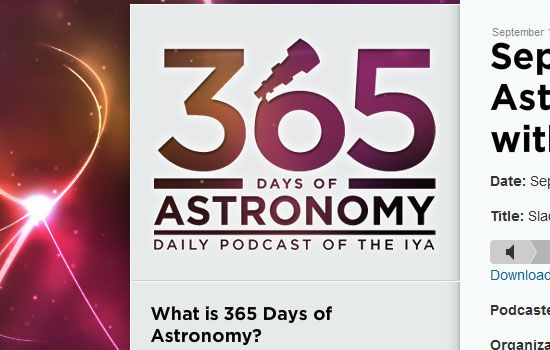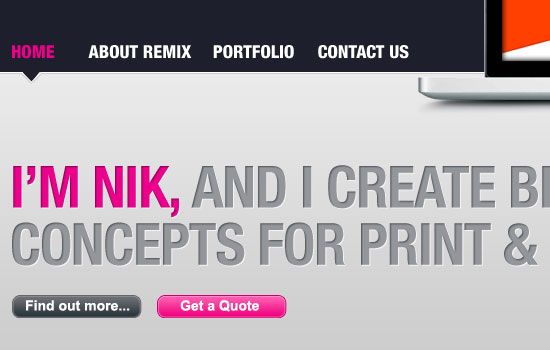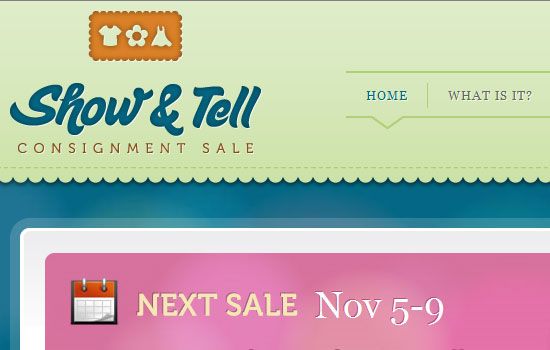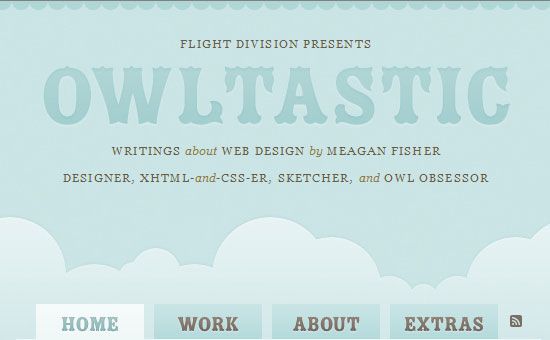
Existen muchas técnicas para poder adornar la tipografía de nuestro sitio. Una de ellas es el grabado de tipografía, un efecto para grabar la tipografía en una superficie, que también podemos crear con CSS3. Cuando esta técnica se usa de forma adecuada, nuestro sitio lucirá original y agradable a la vista. Tener inspiración para desarrollar esta técnica no viene mal, así que os mostraré a continuación una lista de bonitos ejemplos de grabado de tipografía:
1. Epic Event
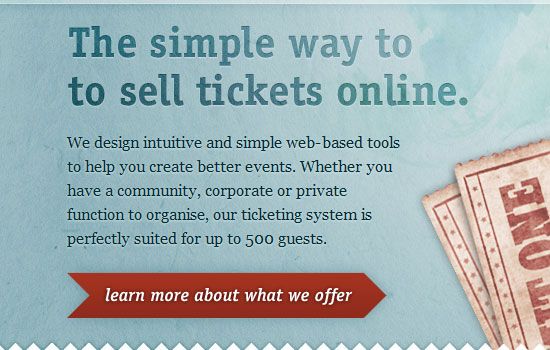
2. Remix Creative
3. Show & Tell
4. Graphik
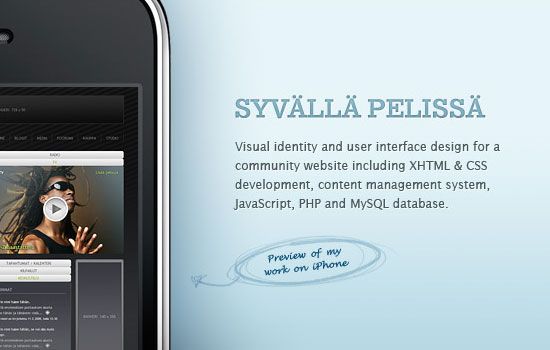
5. 365 Days of Astronomy
6. Owltastic
7. Sarah Longnecker
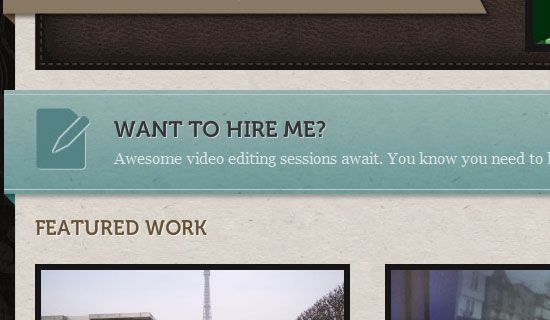
8. Mike Matas Blog
9. For A Beautiful Web
10. MetaLab
11. Helmy Bern
12. NOSOTROS
13. Campaign Monitor
14. Thuiven
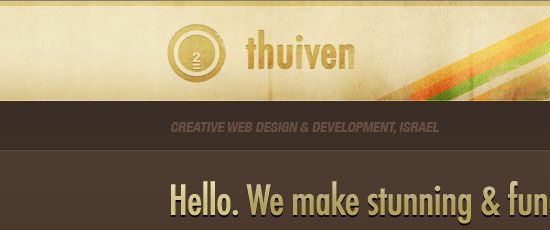
15. Apple
16. Postbox
17. Digimurai
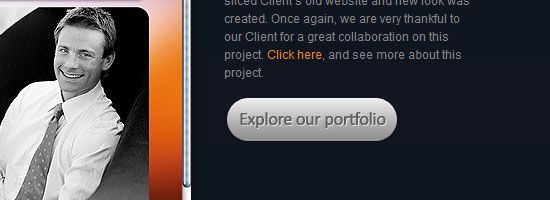
18. Common Good Radio
19. Marc Mendell
20. 280 Slides
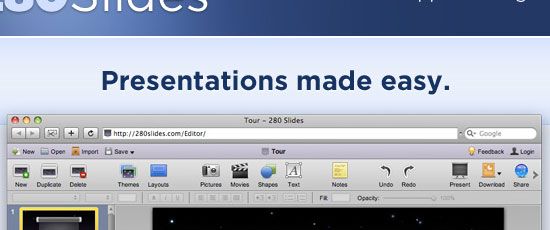
21. Deaxon
22. Bohemian Coding
23. Bravura Coaching & Image